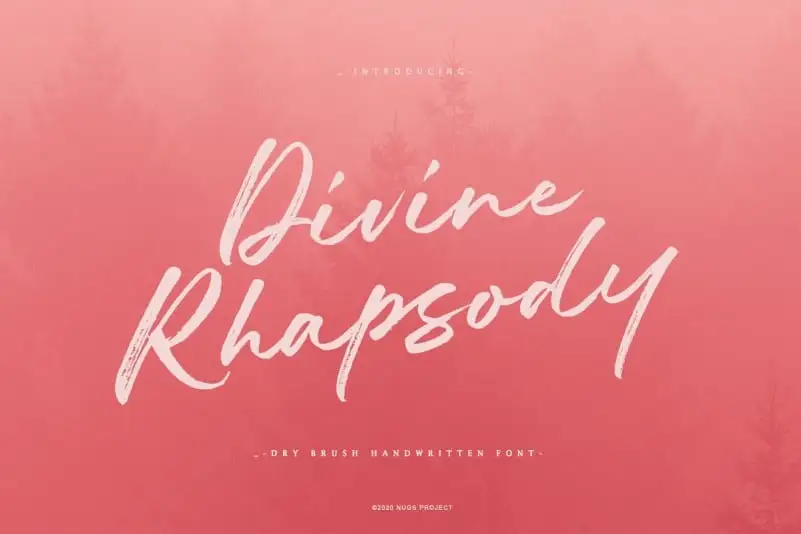
Divine Rhapsody Brush Font – Fonte Grátis
Divine Rhapsody Brush Font
Divine Rhapsody Brush Font é uma fonte de display casual criada a partir do uso de um pincel seco com passadas rápidas, resultando em desgastes naturais que dão ao texto um toque único e elegante. Esta fonte perfeita para assinaturas, marcas, casamentos, moda, títulos em fotos, outdoors, banners publicitários, capa de livros, embalagens, citações escritas a mão, cartões de agradecimento e anúncios. Com todas as letras maiúsculas e minúsculas, números e pontuação, esta fonte está disponível tanto em otf quanto ttf formatos. Ideal para qualquer projeto que busque um toque autêntico e criativo, seja em design de gráficos ou criação de conteúdo digital. Seja ele uma assinatura elegante na sua logo personalizada, uma capa de livro com um visual único e charmoso ou até mesmo um cartão de agradecimento personalizado – Divine Rhapsody Brush Font é definitivamente o tipo de font que tornará seus projetos ainda mais impactantes.